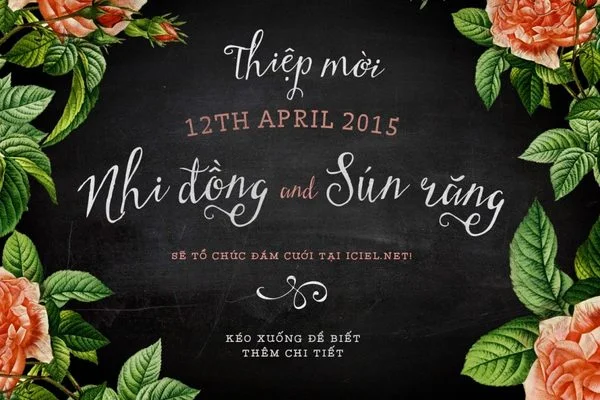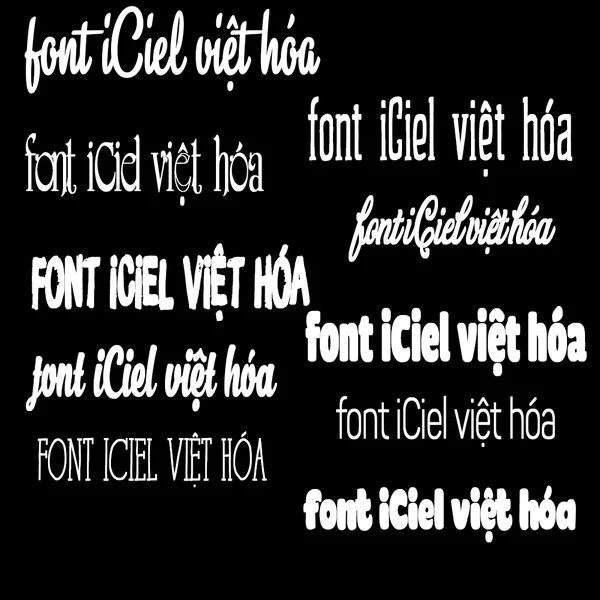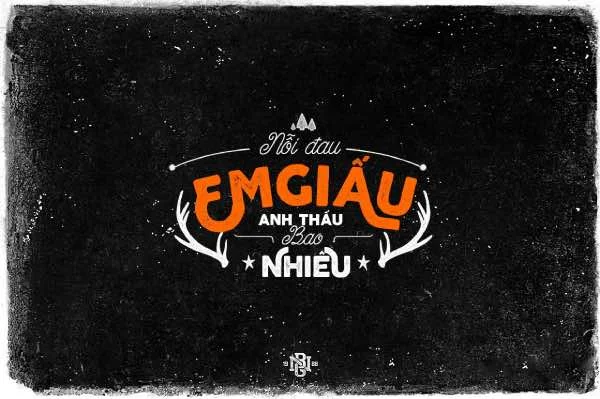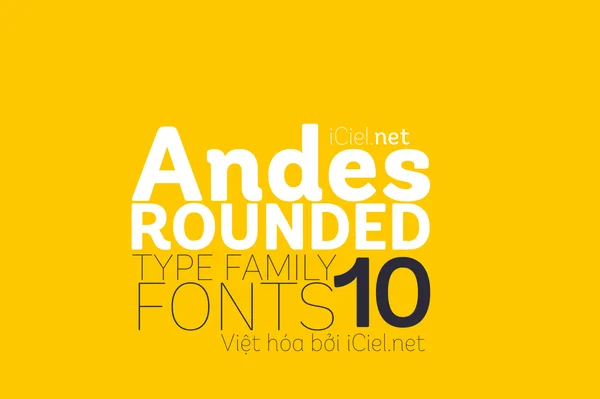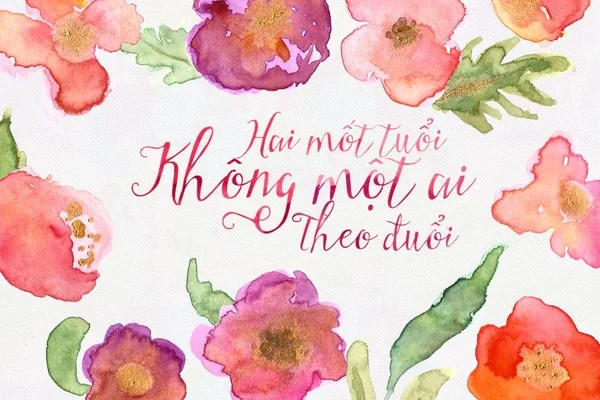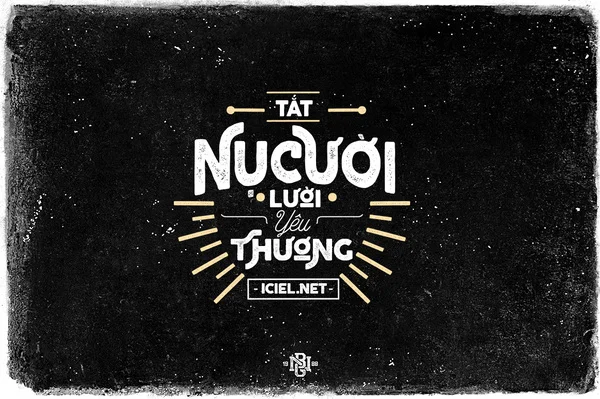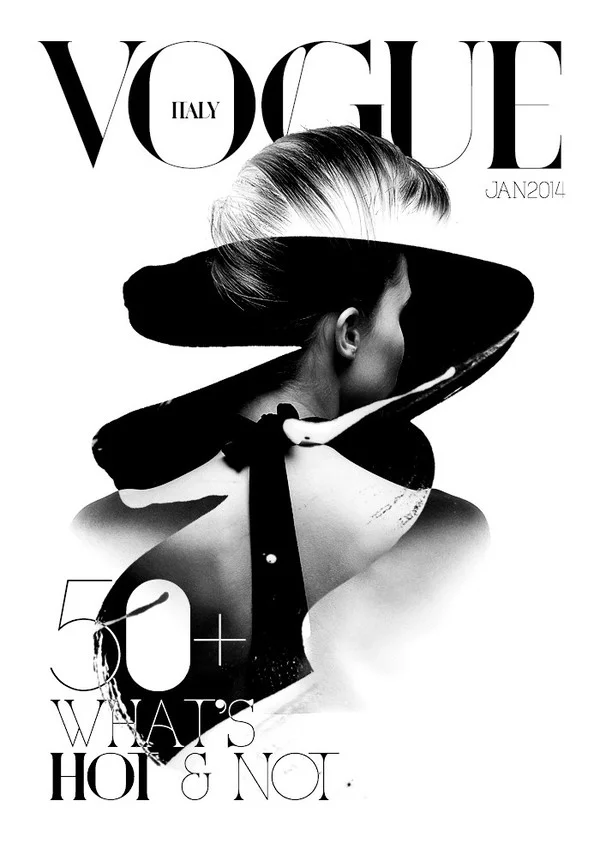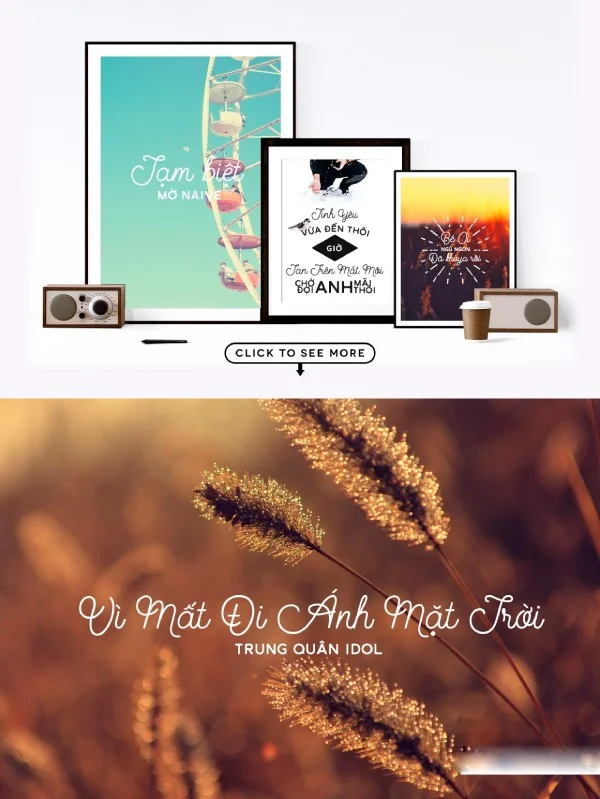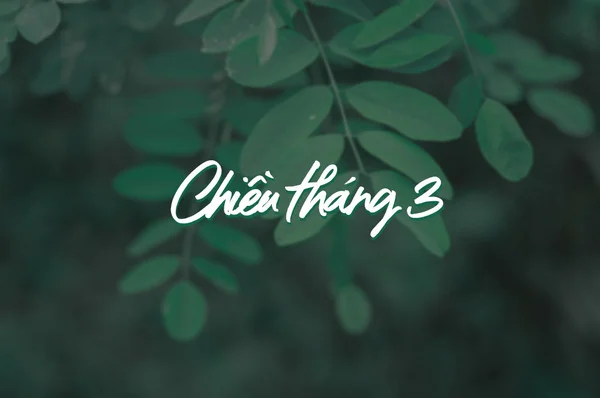
Font iCiel là một font chữ đẹp và quen thuộc với nhiều designer. Cộng đồng designer Việt Nam đã quá quen thuộc với “ông lớn” iCiel, đặc biệt về loạt Việt hóa và những bộ phông chữ đậm chất cổ xưa. Tuy nhiên, có rất nhiều điều thú vị xoay quanh iCiel font. Vì vậy, Printgo sẽ giới thiệu sơ lược về iCiel font và gửi đến các bạn link tải font iCiel đẹp và mới nhất ở cuối bài.
Font iCiel hay iCiel font dùng để nói về các font chữ do diễn đàn chuyên về thiết kế nổi tiếng iCiel Việt hoá. Đây là một diễn đàn có sự tham gia của rất nhiều người đam mê đồ hoạ. Phần lớn những font chữ được Việt hóa được gắn tiền tố iCiel - kèm tên gốc của font. Cần lưu ý rằng không phải tất cả iCiel font Việt hoá đều miễn phí.